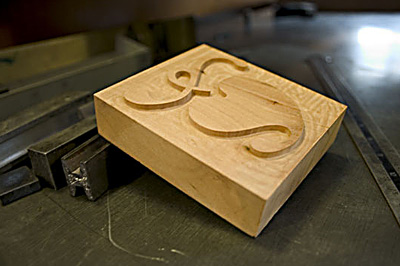
Buchdruck-Holzlettern und typographische Umsetzungen
das ging vor ein paar wochen durch alle foren durch, es schadet aber nicht noch einmal darauf hinzuweisen, es kann für viele eine inspiration sein.
und ein designbüro sie arbeiten zwar digital aber bringen oft den charme rüber.
das gin vor ein paar wochen durch alle foren durch, es schadet aber nicht noch einmal darau hinzuweisen, es kann für viele eine inspiration sein.
Ja, wir Bleisatz- und Buchdruck-Leute leben in einem anderen Zeit-Kontinuum. Da dauert es schon etwas länger, bis es aus allen anderen Foren zu uns ins Bleisetzer-Forum schwappt ;-)
und ein designbüro sie arbeiten zwar digital aber bringen oft den charme rüber.
… mit digitaler Technik den ‹Charme› der Holzdruck-Oberflächen nachgeahmt – irgendwie schon merkwürdige Zeit. – Es gibt doch eine – berühmte – amerikanische Druckerei, die Konzertplakate mit Holzlettern druckt, habe den Namen vergessen.